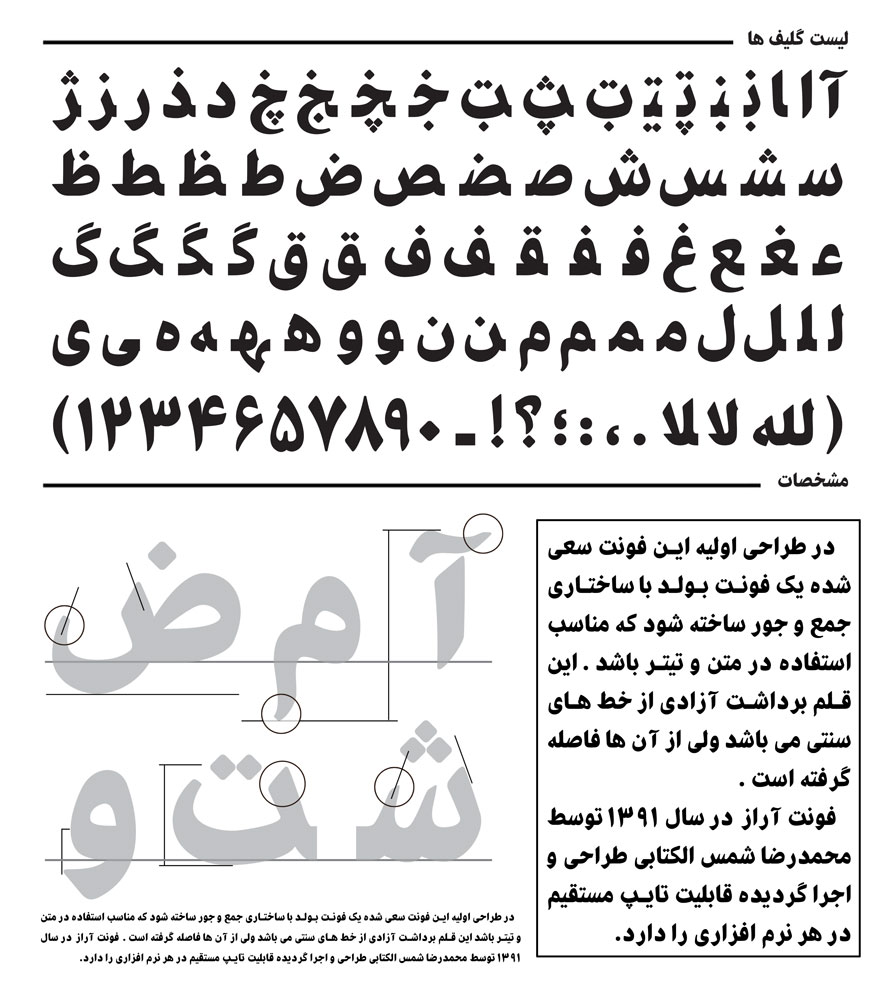
فونت زیبای آراز
فونت آراز / طراح : محمدرضا شمس الکتابی
فونت زیبای آراز یکی از فونت‌های زیبای فارسی است . فونت آراز ، برداشت آزادی از خط‌های سنتی می‌باشد ولی از آن‌ها فاصله گرفته است . این فونت توسط محمدرضا شمس الکتابی در سال ۱۳۹۱ طراحی و اجرا شده است و قابلیت تایپ مستقیم در هر نرم‌افزاری را دارد . امیدوارم مورد پسند شما ، عزیزان قرار گیرد و آن را دانلود نمایید .
فونت آراز / Araz Font
پیش نمایشی از فونت زیبای آراز